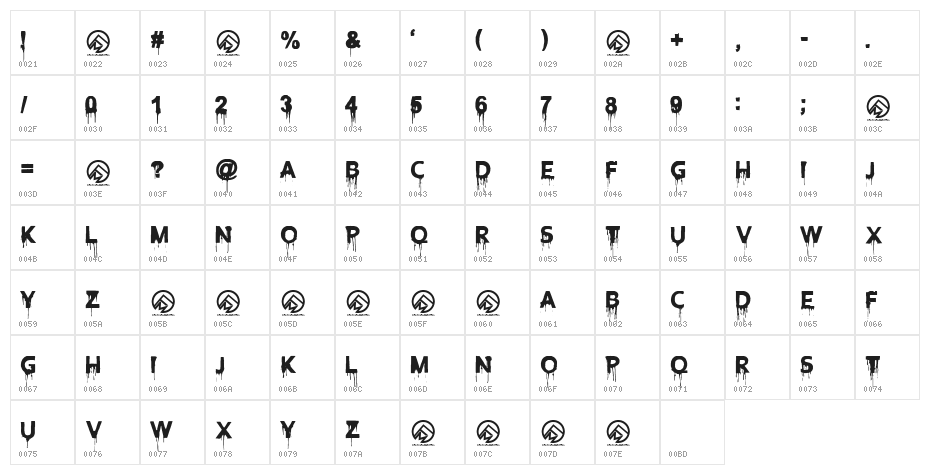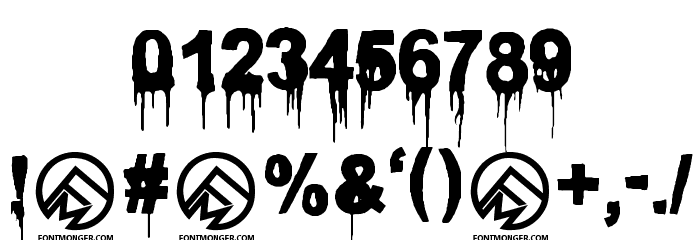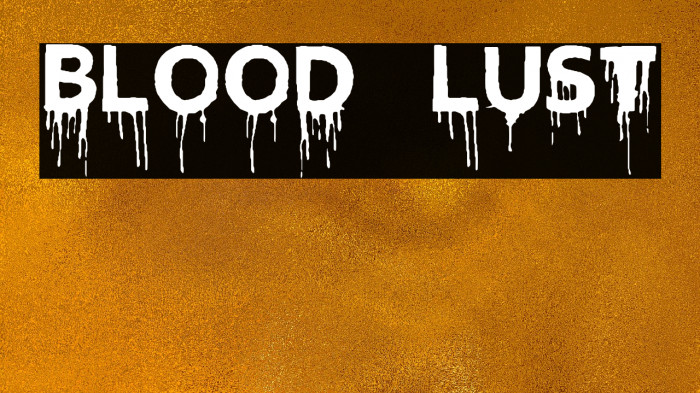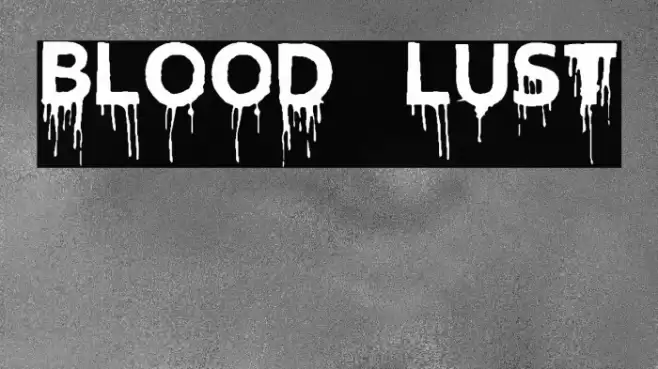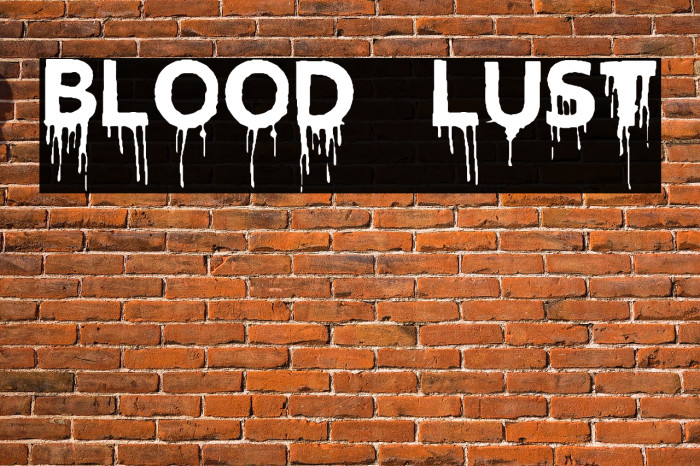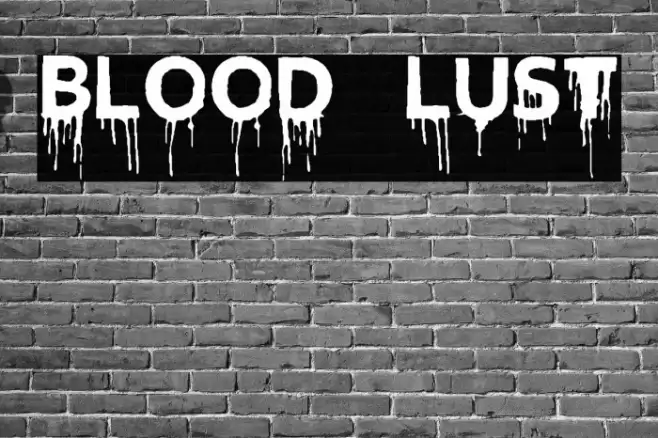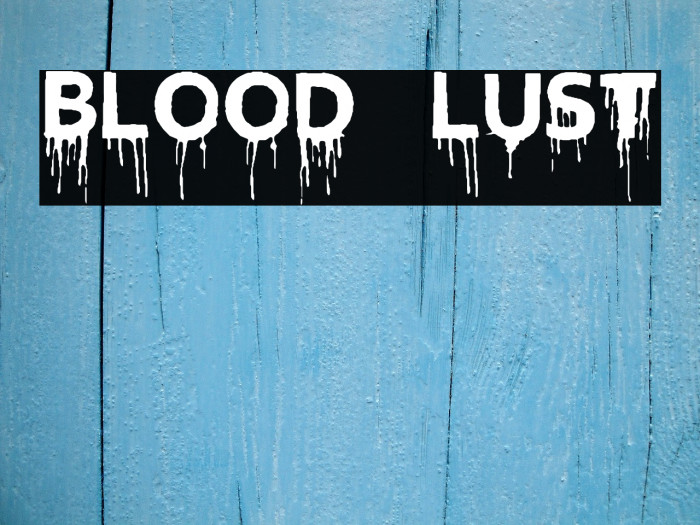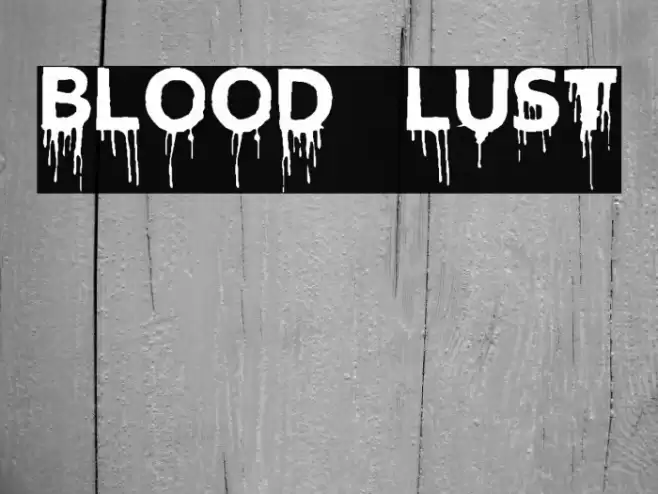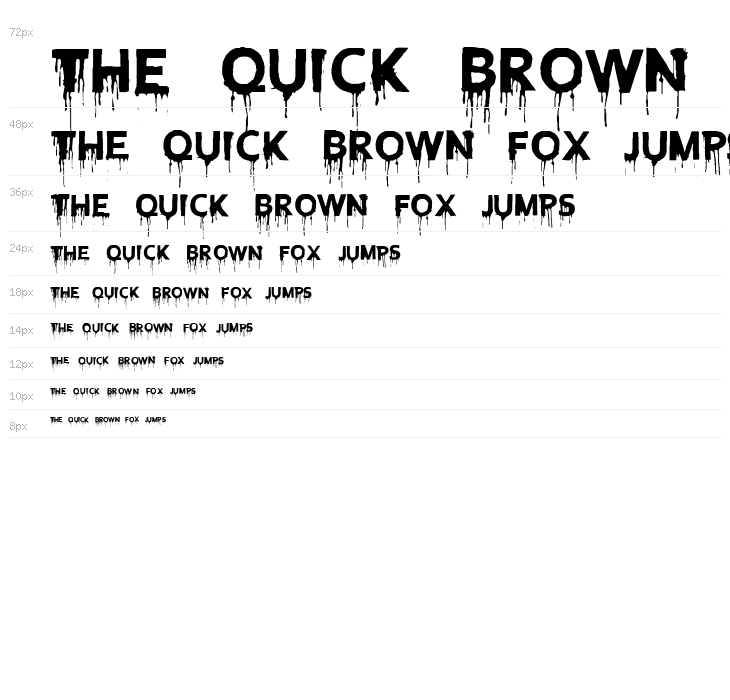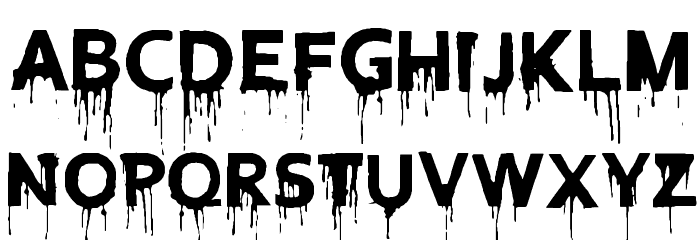
Blood Lust Font
| Caso de uso | Headlines, Posters, Themed Events |
| Proyectos propuestos | This font is perfect for Halloween-themed projects, horror movie posters, haunted house flyers, or any design that requires a chilling and dramatic effect. |